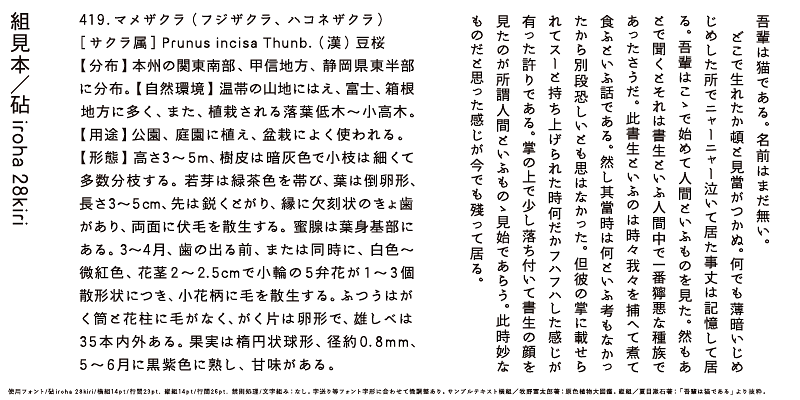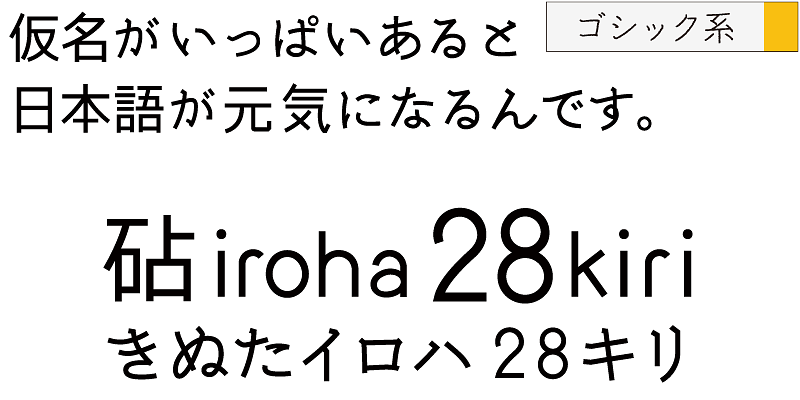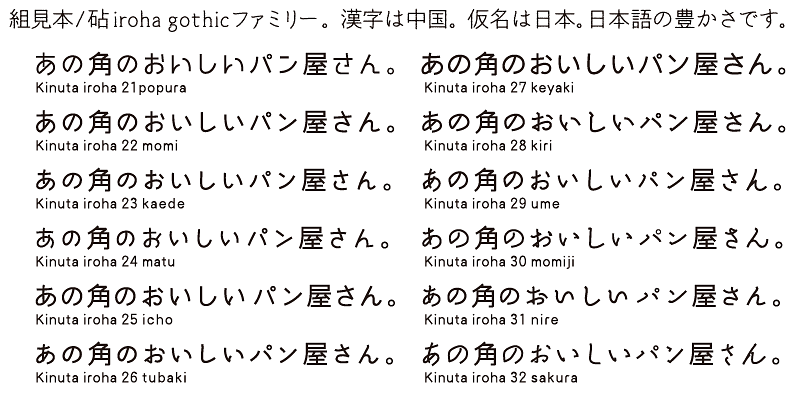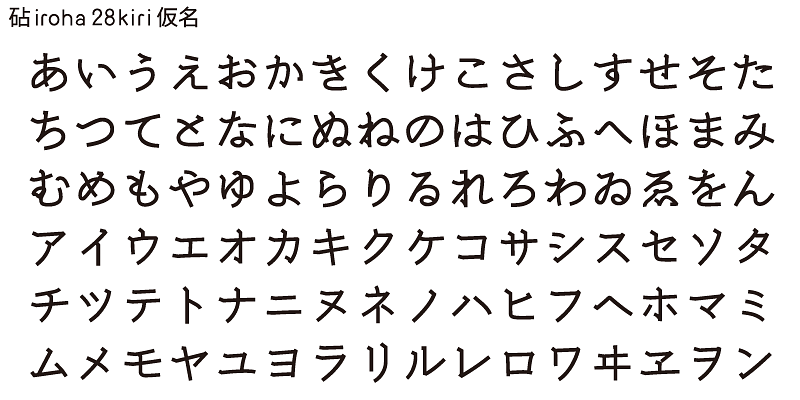
iroha 28kiri tiene la sensación de ser una escritura a pincel con caracteres kana ligeramente comprimidos verticalmente para dar un aspecto sólido y anticuado.
Una característica del japonés es que tiene caracteres silábicos llamados kana. Los caracteres kana se inventaron para representar sonidos en japonés y traducir textos importados de China. Los caracteres kana son necesarios para crear palabras y expresiones japonesas a partir de caracteres ideográficos kanji, que son caracteres chinos. Si bien puede haber ambigüedades, estas palabras y expresiones exhiben la cercanía y amabilidad de las personas que viven en la pequeña y densamente poblada tierra de Japón.
Kinuta Font Factory cree que los caracteres kana son el origen de las palabras escritas en japonés, y que mejorar los caracteres kana hará que el texto japonés sea más atractivo. En promedio, el 60 % del texto japonés se compone de caracteres kana; cambiar la forma de estos caracteres cambia la apariencia visual del texto. Las posibilidades de expresión tipográfica utilizando caracteres kana sencillos, dinámicos y curvilíneos son enormes, y la riqueza del texto japonés depende de ellos en gran medida. Esta es la razón por la que Kinuta Font Factory ofrece muchas variaciones de tipos de letra kana.